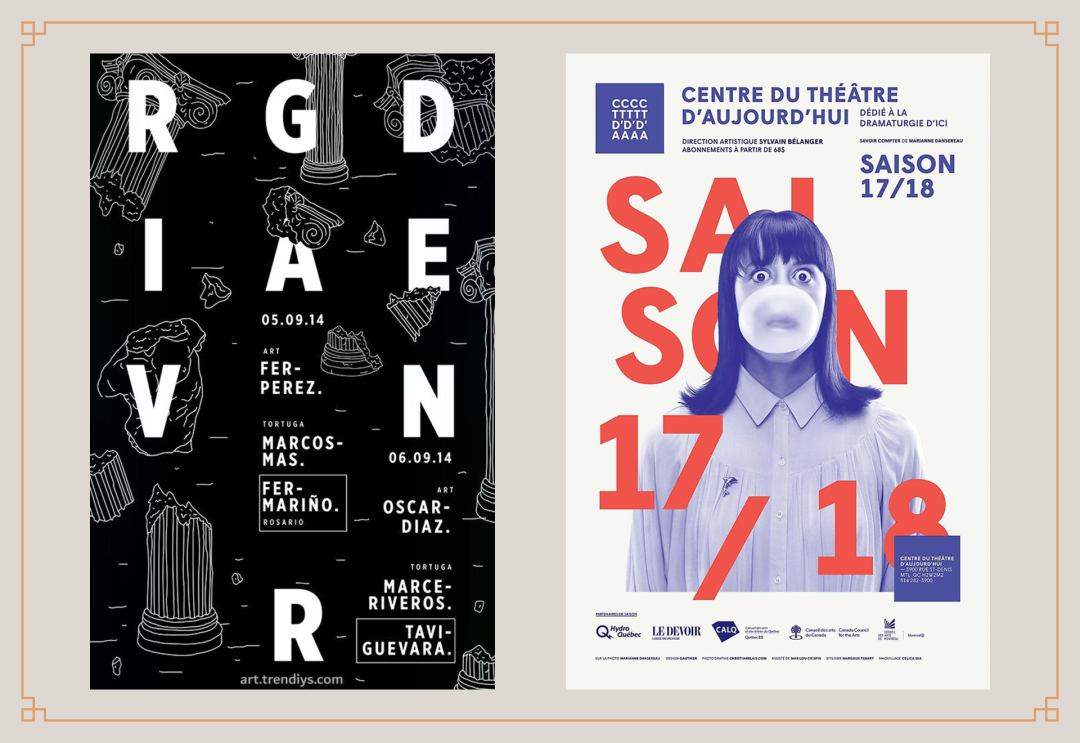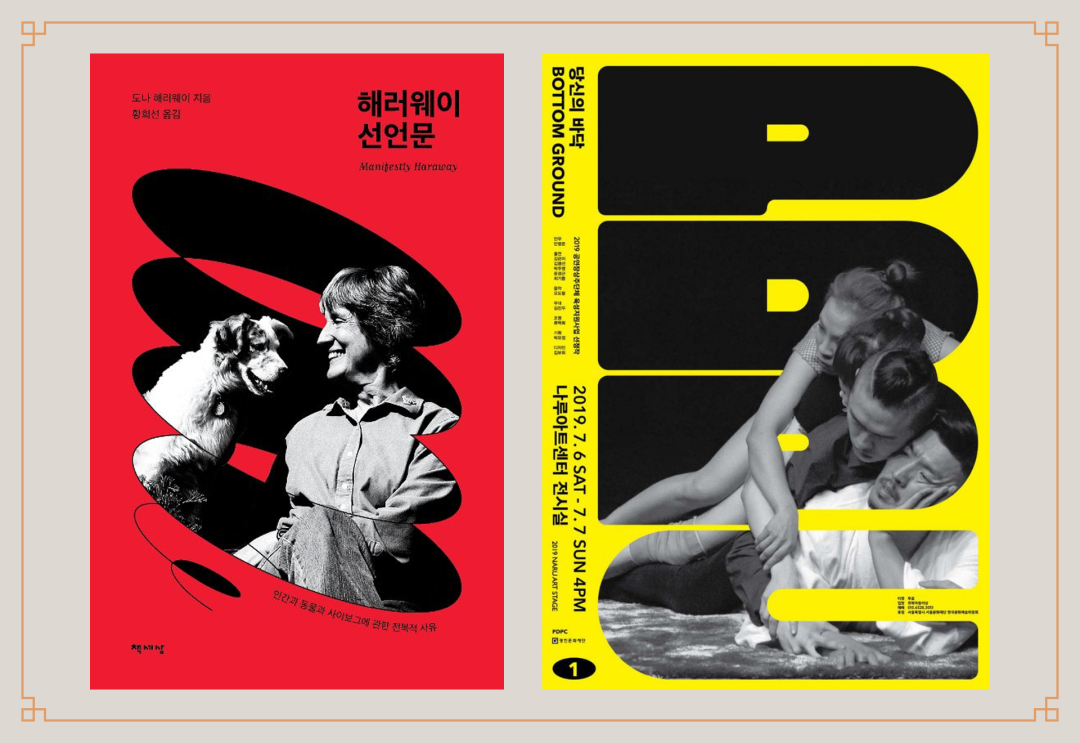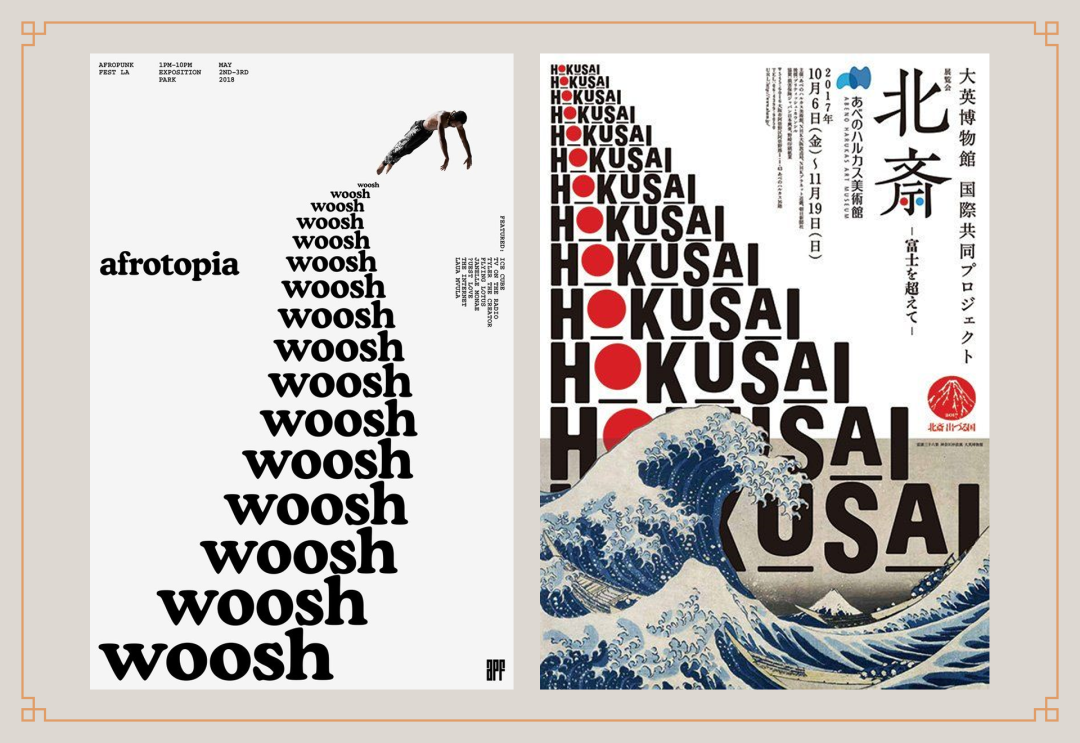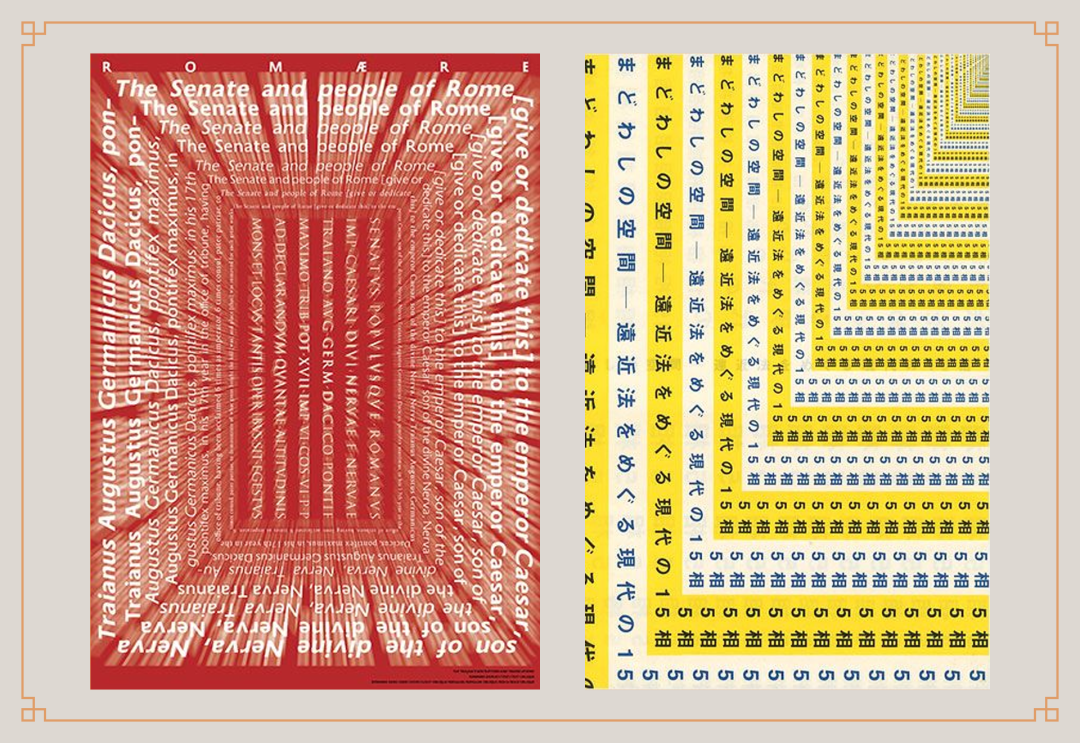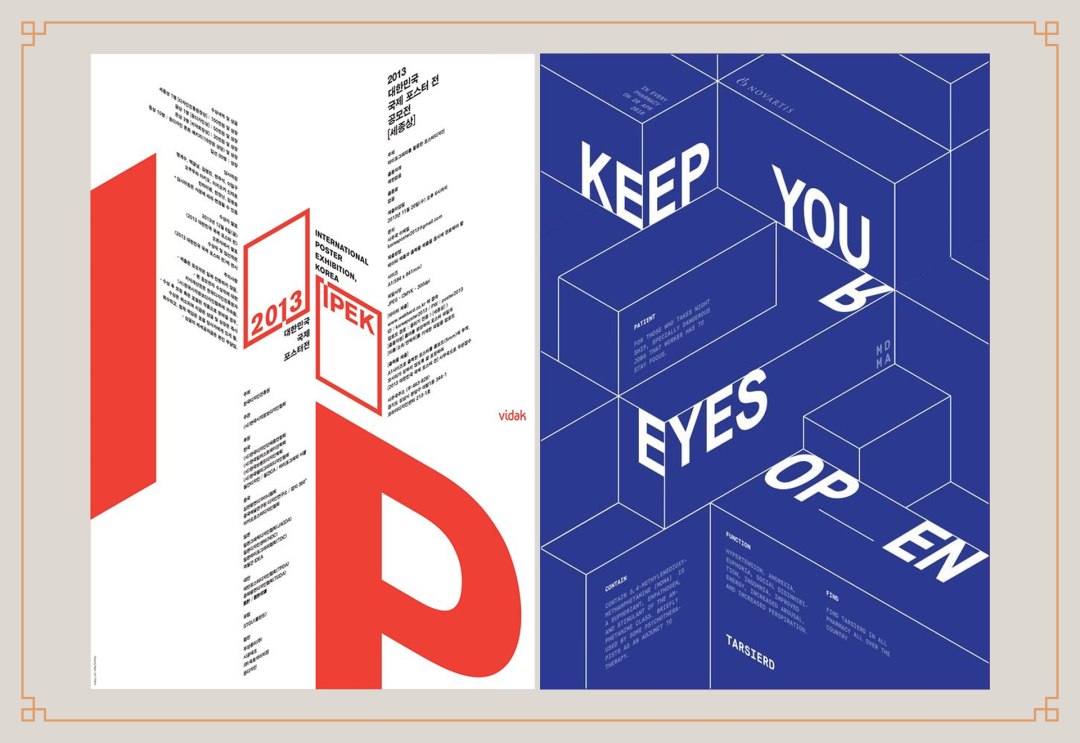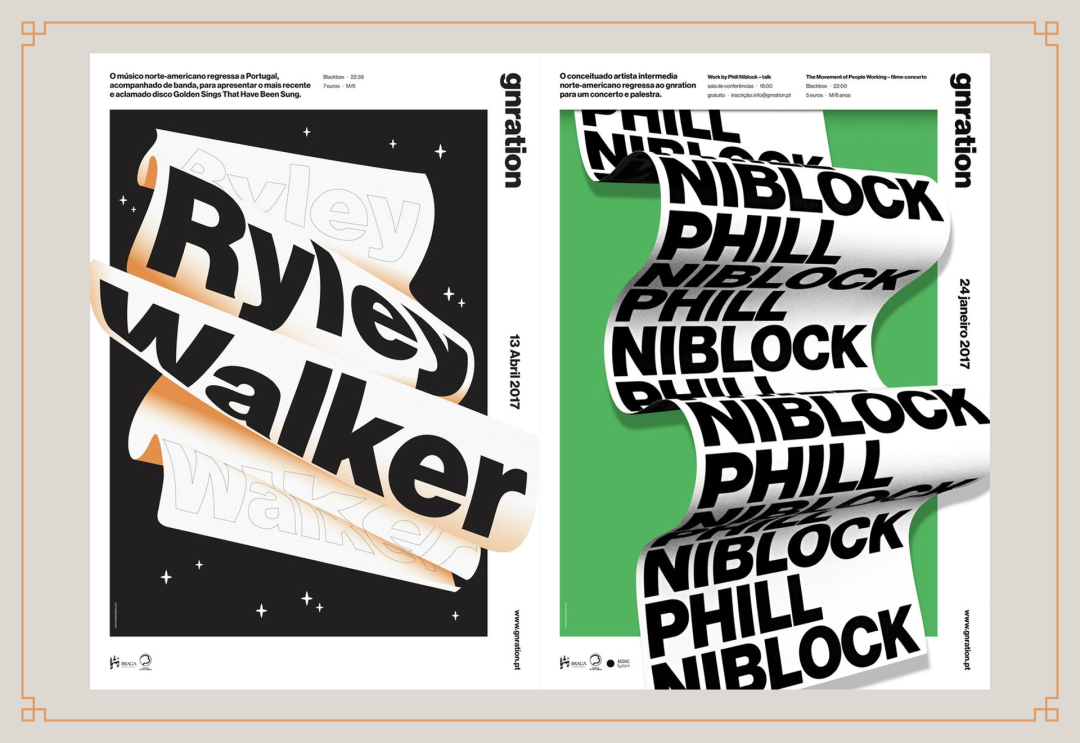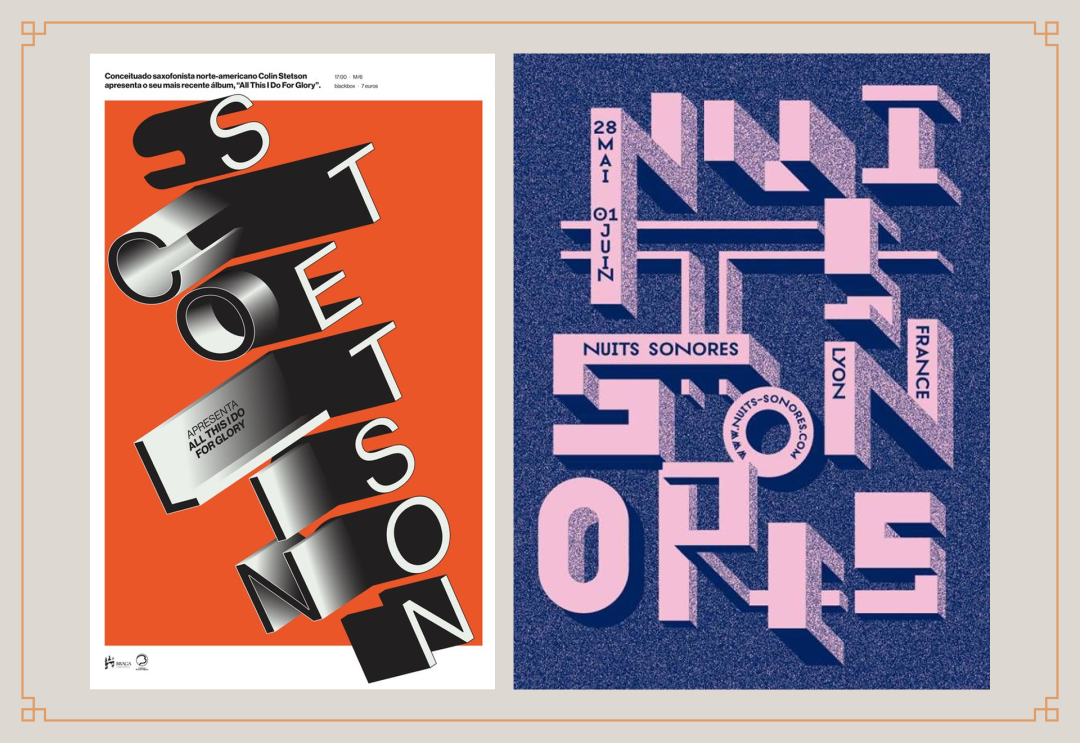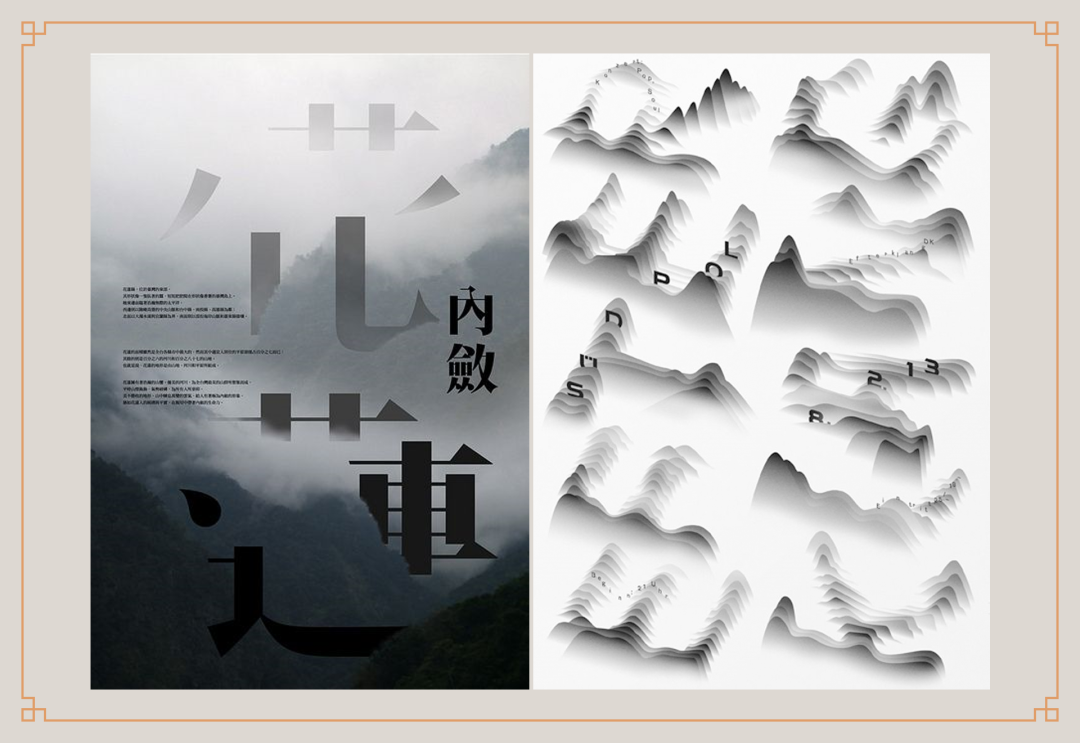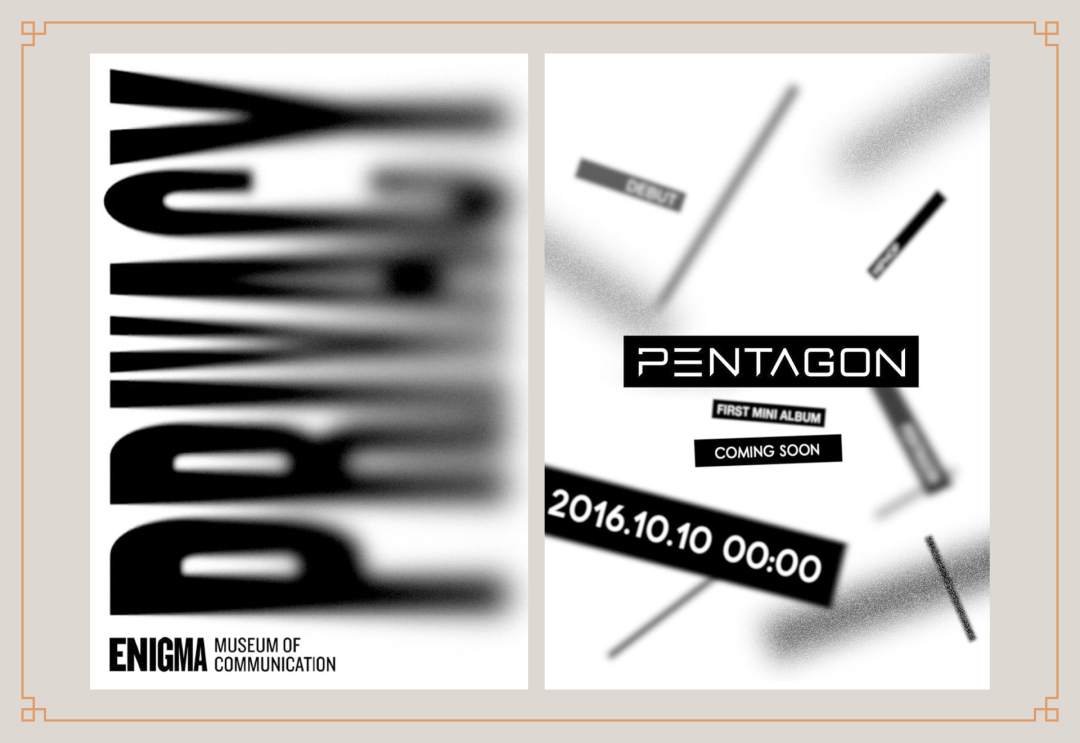
如何提升设计中的空间感!给你分享9个方法
空间感是指艺术形象通过一定手法引起的类似现实空间的审美感受。包括作品直接表现的空间和作品具体形象之外的使人想象到的空间。这种空间感,一定程度上决定着版面的视觉效果与美感。巧妙的利用空间,可以集中观众的注意力,丰富的层次感使作品更具观赏性,同时又可以让作品主次分明,更有效的传达信息。
通过对设计作品的参考分析,设计师深海总结了营造空间感的方法,大致分为以下九个类别,希望这篇文章能对大家有所帮助。
一、遮前掩后
“遮前掩后”的意思是:通过画面设计元素之间的遮挡,交代空间关系,从而产生一定的空间感。这种形式可能空间感较弱,但易于表达,可以使文字和图片更好的结合。
设计时为了保证信息的传达,普遍会选择将文字信息完整的展示出来。其实像上面两个案例一样,适当使用遮挡关系,反而能让文字与图像结合的更好。
人的大脑有“惯性阅读”的能力,这使得即使文字被遮挡,也不会影响太多识别性。
利用蒙版,然后局部破出,这也是营造空间感常用的手法。本质上,这也属于使用遮挡关系的一种方式,这种效果空间感更强,让观众有一种打破次元壁的感觉。
使用这种样式时需要注意:用作蒙版的图形或文字,必须简洁,并且识别性足够高,否则会影响信息的传达。
二、以小见大
“以小见大”指的是:利用近大远小、近疏远密的基本透视原理,来营造空间感的一种方式。
在平面设计中,面积大的元素使我们感觉更近,面积小的感觉更远,即使是单一的设计元素,只要遵循基本的透视原理,也能塑造出空间感。
从这两个案例可以看出,元素的面积大小变化越大,空间的纵深感就越强;通过控制元素之间的位置关系,可以使空间看起来平整或者曲折,表现力非常丰富。
三、山重水复
“山重水复”是“以小见大”的进阶版,同样是利用近大远小的物理规律,塑造空间感。不同的是,通过元素的无限重复,会让空间感更强,对排版的把控能力也要求更高一些。
重复的元素会让画面有很强的冲击力,强烈的空间感让观众仿佛在无限的跌落。使用这种版式一定要注意近疏远密的空间关系,否则会降低画面的可信度。
四、横峰侧岭
“横峰侧岭”是指:通过变形,改变元素的透视,在整个版面中塑造多个平面,以此来增强作品的空间感。
将同一平面的元素对齐,创造出虚拟的边界线,借助这些参考线来塑造不同方向的平面。如果觉得空间感不够强烈,可以借助辅助线加强透视。使用这种形式的重点在于,要注意阅读顺序和空间平面之间的关系,不要为了画面,一味地堆砌空间,信息的传达永远都是最重要的。
最近非常流行的立体效果,因为空间感强,很容易出效果,深受设计师们喜爱。其实这种类型也是通过透视和多个平面来塑造空间感,制作时大多需要3D软件进行辅助,才能实现如此真实的透视效果。
五、冰厚三尺
“冰厚三尺”指的是通过给元素添加厚度,增强元素的立体感,从而提升空间感。这是一种非常简单粗暴的方式,立体化后的元素,可以展现更多的角度,使排版方式更加多变,画面也更加灵动。
最常见的2.5D风格,去除了透视感,依靠立体元素来营造空间感,可以使整个版面更加稳定和谐。有些设计师还会引入矛盾空间,让设计作品看起来更有趣味性,吸引用户目光。
六、潜踪隐迹
“潜踪隐迹”的意思是:通过改变透明度,模拟雾中的物体,距离越远的元素可见度越低,从而营造出空间感。
在中国传统国画中,就会通过控制水墨的浓淡,来展现画面的空间感。因此这种方法很适合中国风的设计,让整个作品富有神秘、幽寂的气质。
七、雾里看花
“雾里看花”和“潜踪隐迹”很相似,通过虚实的变化,模拟现实世界中的景深效果,从而塑造空间感。这种方法是最常见的,也是最出效果的,在塑造空间感的同时,还可以强调主体信息。
在对版面元素进行模糊处理的时候,要考虑元素与焦点的位置关系:距离焦点越远,模糊程度越高,普遍情况下,会将最主要的视觉元素作为焦点,保证信息的准确传达。
八、浮光掠影
有光的地方就存在影子,投影本就是空间感的一种直接反应,“浮光掠影”就是利用光影的变化,在平面中营造视觉上的空间感。
光影的变化非常丰富,因此,光影的表现方式也是五花八门。殊途同归的是,所有的光影都是为空间感服务的,所以大多数情况下,都要遵循现实世界中的规律,确定一个光源,保证整个画面的光影统一。
九、镜花水月
随着软件功能越来越强大,重现现实世界越来越容易。“镜花水月”指的就是:参考现实世界的折射、反射等自然现象,在平面空间塑造空间感。这种方式看起来质感很强,效果也非常酷炫。
需要注意的是:在设计之前一定要考虑好效果与内容的关系,一味的堆加效果,除了炫技毫无价值。
总结